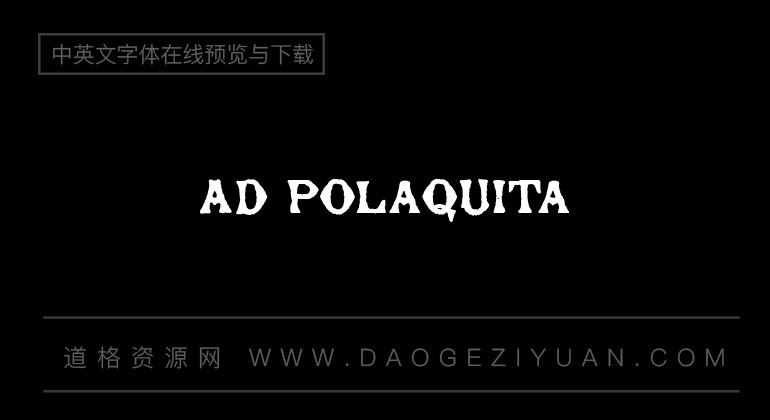
AD Polaquita
AD Polaquita 是由著名的设计师 Adrian Frutiger 创作的一款现代字体。它是一款细节丰富的字体,具有精致的线条和大胆的设计,为文字添加了浓厚的视觉效果。此外,它还具有良好的可读性,可以用于一些特定的应用场景,如标题、封面、新闻报道等。
AD Polaquita是一款非常不错的手写艺术字体,具有很好的视觉感,适合于文化类的宣传设计、商业类品牌的广告和产品包装设计以及个性化文字排版等较多场景。